VNOM MAG
VNOM Mag es una representación latente de todo aquello que nos rodea, un tributo a la bella cotidianidad de nuestros días. La tipografía fue el medio conductor del proyecto, los contrastes tipográficos entre fuentes fueron el punto focal de cada artículo, se crearon tipografías con técnicas manuales y se digitalizaron como parte del proceso creativo, asimismo se realizó experimentación tipográfica con materiales no convencionales.
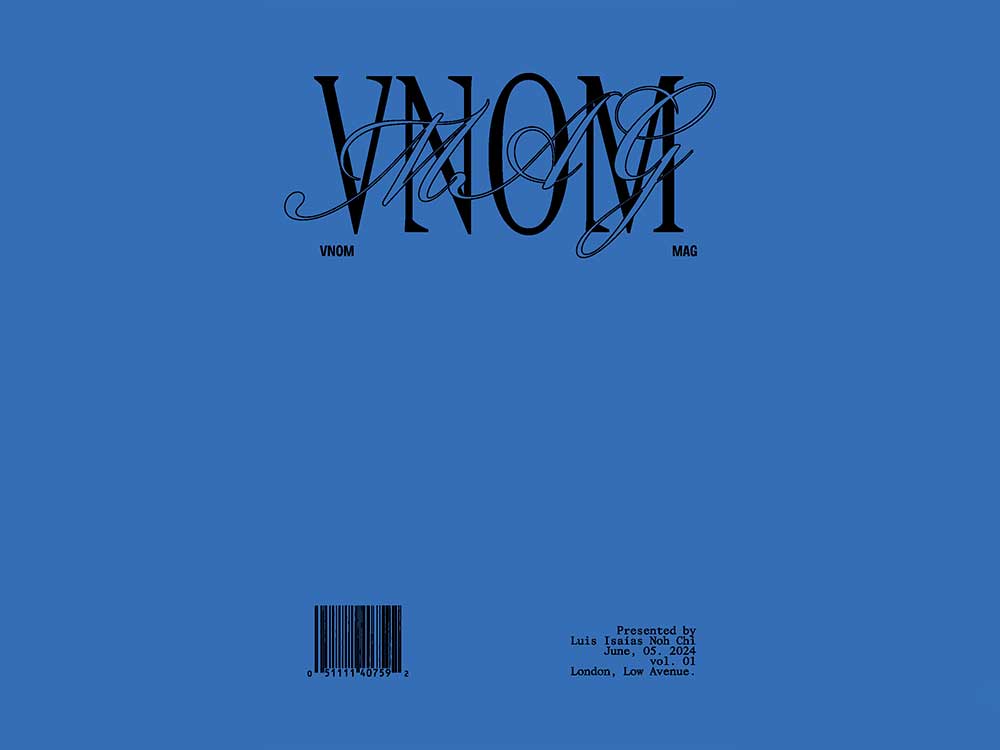
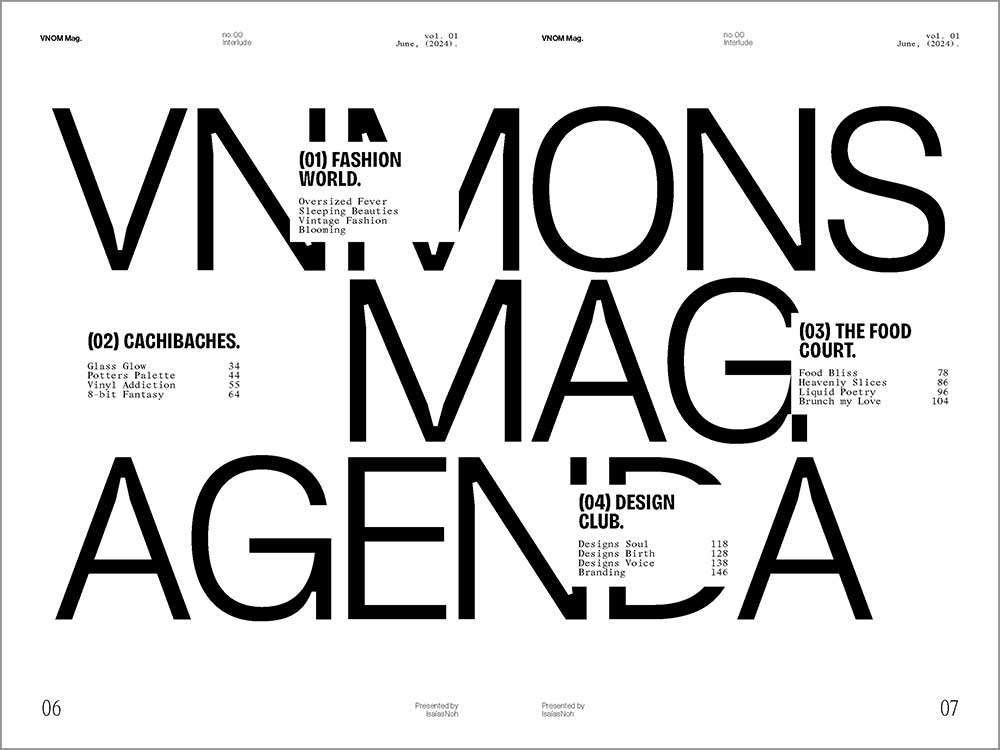
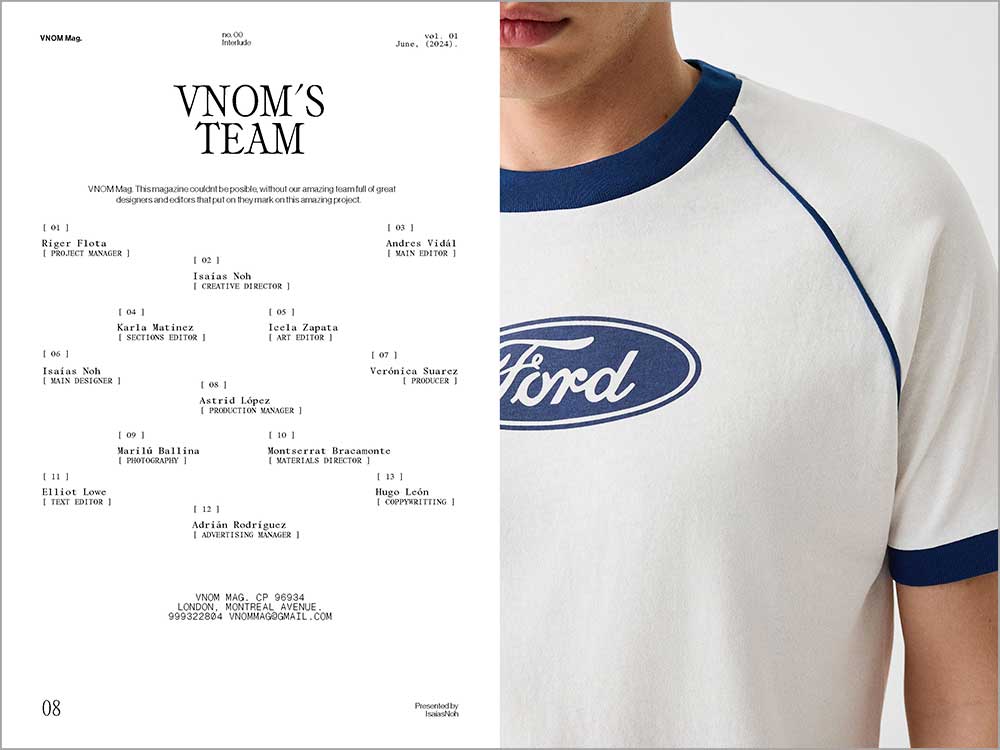
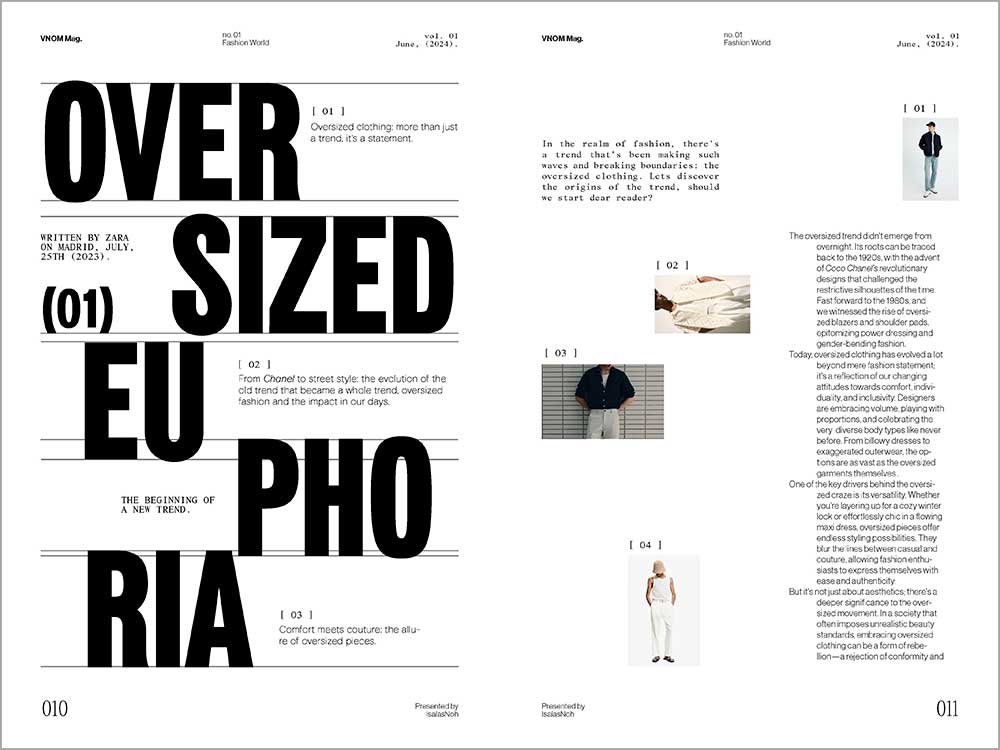
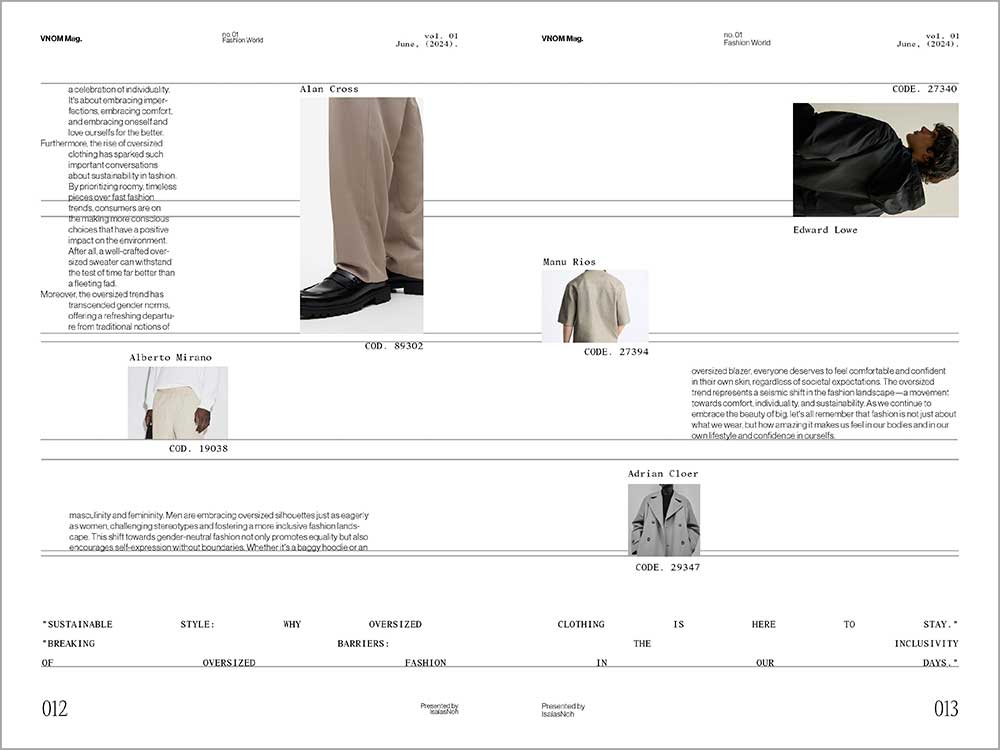
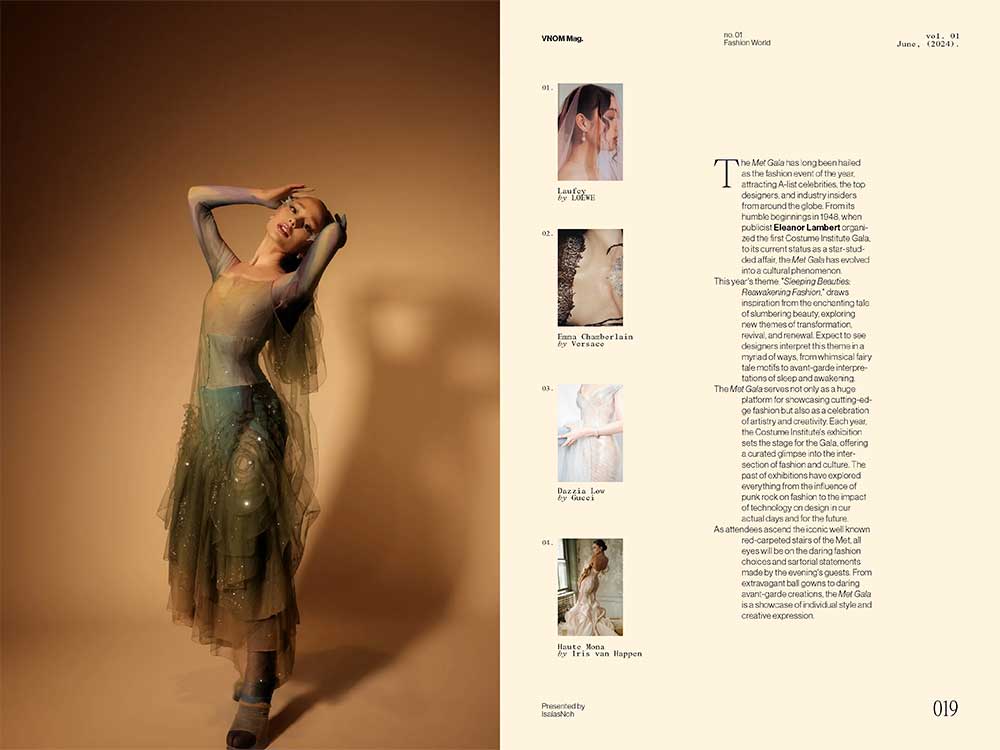
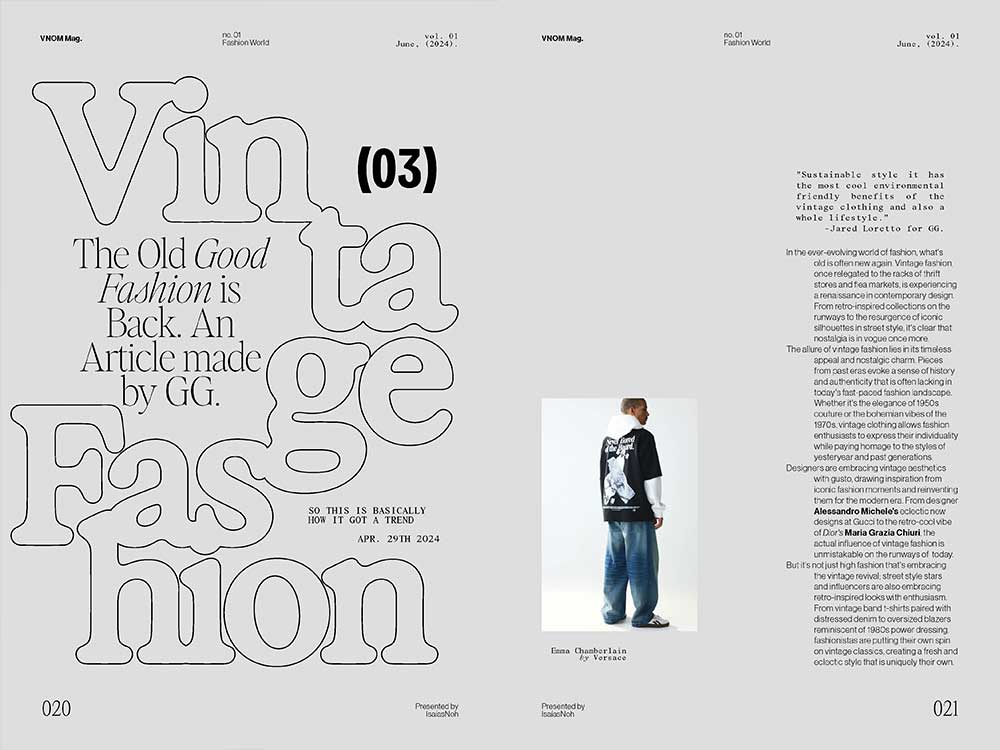
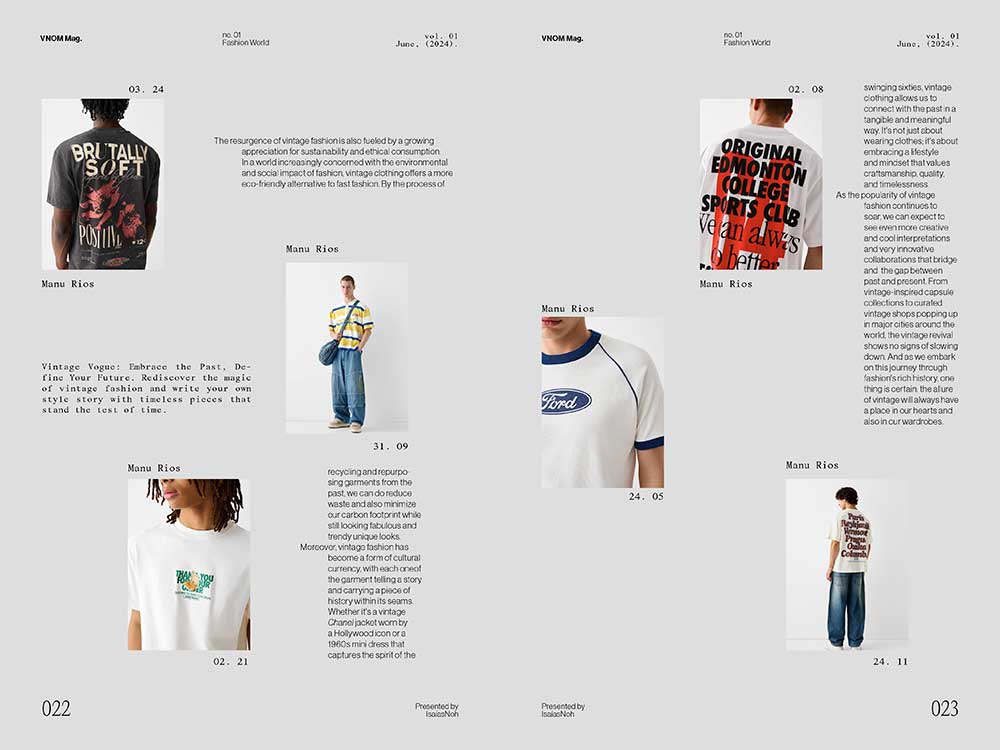
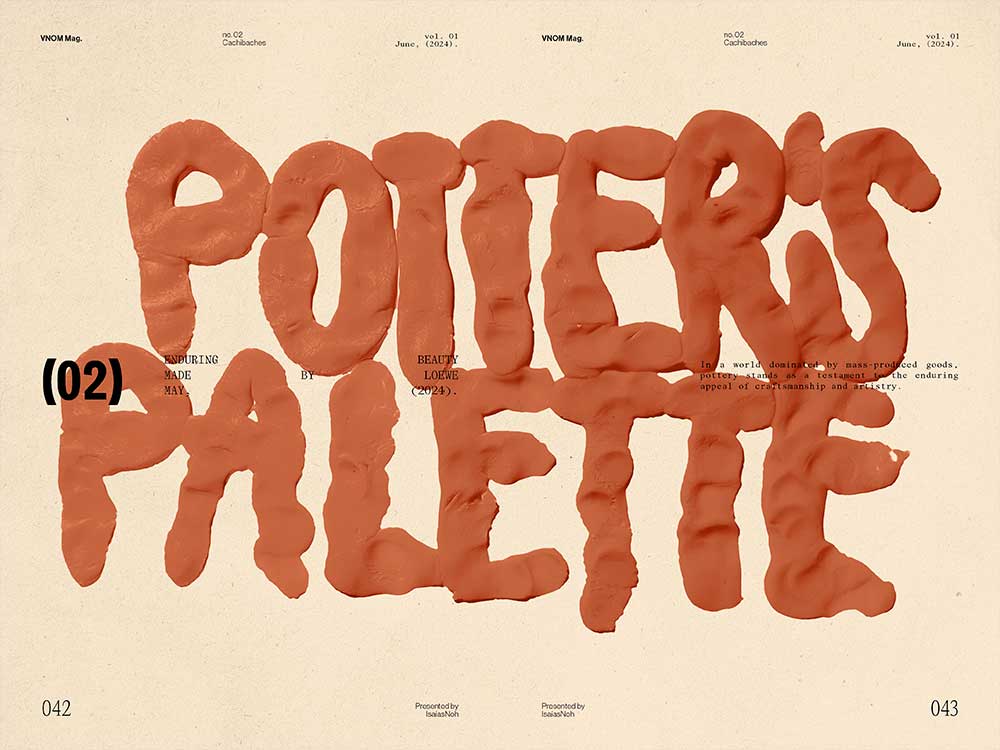
MI DIARIO ARTÍSTICO
Mi diario artístico es una exploración de la tipografía como medio de expresión visual, creatividad y conexión personal. Este proyecto se compone de un sketchbook, un póster y una tote bag que celebran la creatividad y las personalidades de 10 artistas: Pablo Picasso, Salvador Dalí, Katsushika Hokusai, Edvard Munch, Claude Monet, Piet Mondrian, Henri Matisse, Vincent van Gogh, Gustav Klimt y Frida Kahlo. Las ilustraciones fueron diseñadas con formas tipográficas que escriben el nombre de cada artista, integrando frases inspiradoras que reflejan su visión de la creatividad.
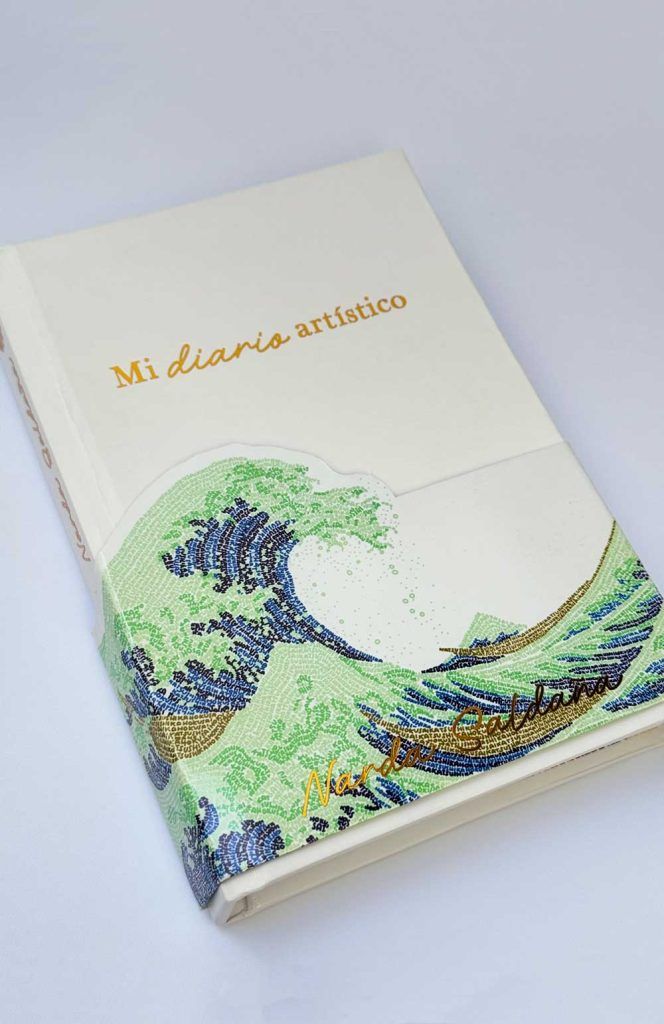
ECHOES MAGAZINE ISSUE Nº1
Revista que celebra el arte en todas sus formas, no solo como una expresión de la creatividad individual, sino también como un eco resonante de nuestra sociedad y cultura. Todas las tipografías escriptas y cursivas fueron hechas a mano con diferentes técnicas digitales y manuales que se digitalizaron posteriormente para su aplicación en las diferentes composiciones editoriales. Las mismas tipografías creadas funcionan como cuerpos de texto independientes y algunos como textura gráfica, haciendo de este proyecto una revista que refleja el arte por medio de la tipografía.
DAMAS LIBÉLULA
Este proyecto expone 10 libélulas mexicanas e invitando al lector a reflexionar acerca del asombro que la vida nos otorga. Este libro se adentra en la magia de estas especies que habitan México, cada una retratada no solo como un insecto, sino como un símbolo de elegancia y misterio. El concepto surge a partir de la intención de integrar arte, diseño, poesía e ilustración. Cada libélula es presentada como una figura casi etérea, con la gracia de una dama.
JOURNAL OF THE TINY WORLD
Este proyecto de exploración tipográfica desarrolla un journal, una tote bag y un póster, todos ellos inspirados en el concepto de creatividad, pero centrándose en los insectos. A través del análisis de formas, colores y principios del diseño, se buscó transmitir la fuerza, el valor y el poder de la tipografía como un elemento principal de comunicación visual, que no solo transmita información, sino que también evoque diferentes emociones. El resultado son 10 ilustraciones, acompañadas de frases que combinan la tipografía con la creatividad y elementos gráficos, mostrando formas que resaltan la belleza y perfección de la naturaleza.